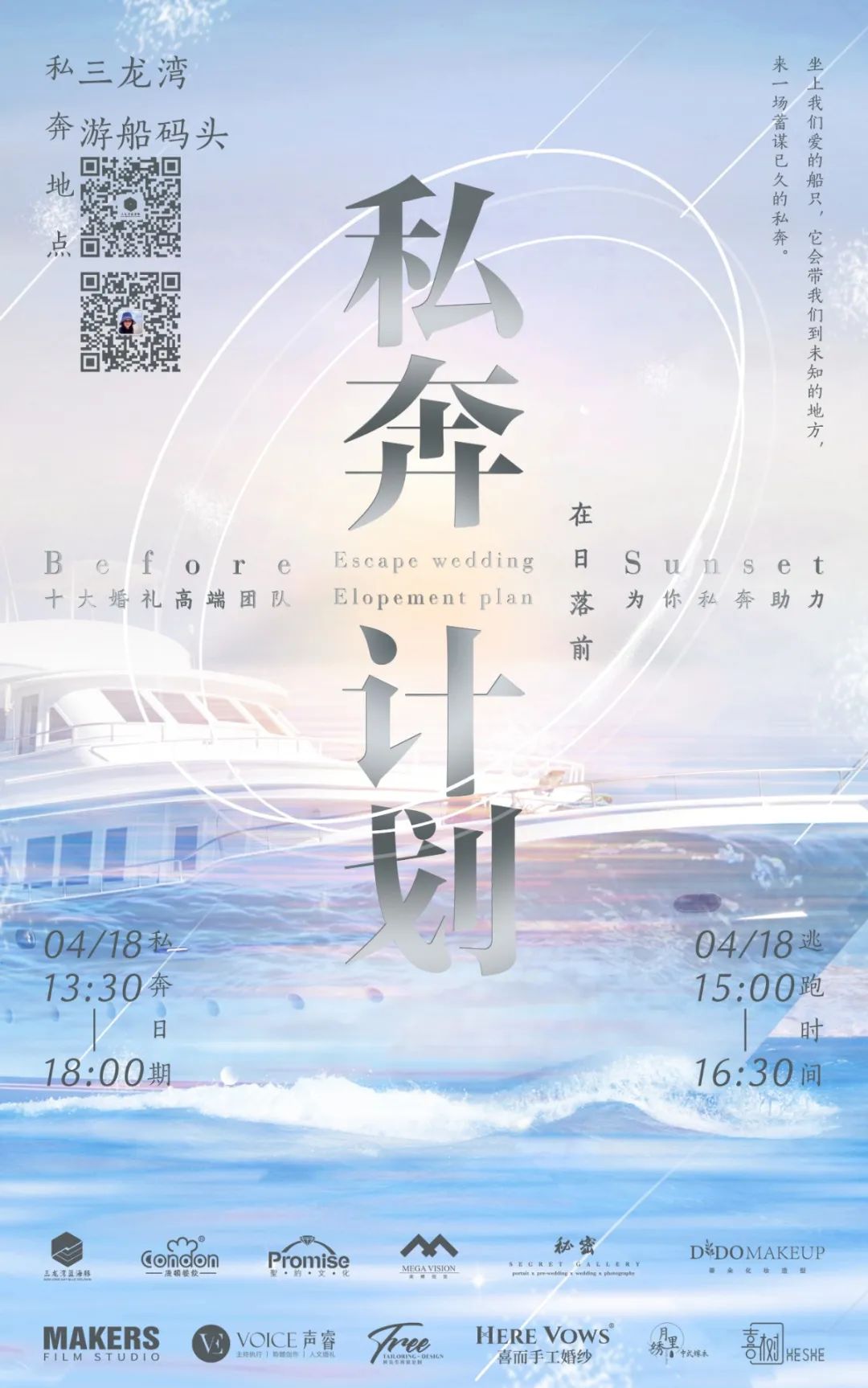
方正文征明小楷
楷书
文征明其人:
文徵明(1470~1559年),明代书家。初名壁(亦作璧),字徵明,号衡山居士。“吴中四才子”之一。擅山水,兼善花卉、兰竹、人物。名重当代,学生甚多,形成“吴门派”。与沈周、唐寅、仇英并称“明四家”。能隶书亦工行、草,尤精小楷。
字体特征:
字体以文征明小楷《落花诗册》为临创开发基础。笔划婉转清丽,温润秀劲、清爽峻拔,结体严谨精密,疏密有致。刚中寓秀,笔画粗细变化自然。
应用场景:
电商、品牌、海报、杂志、书籍、包装、广告、招牌、新媒体、影视、动漫等